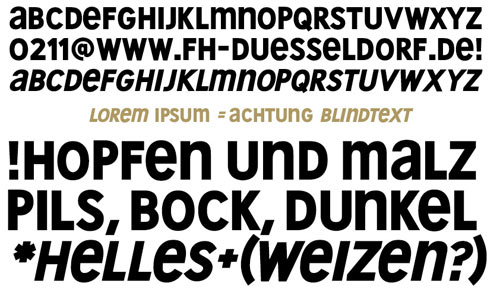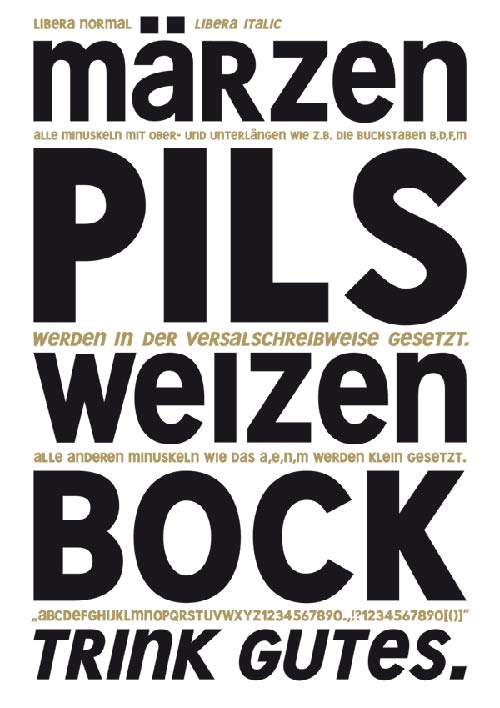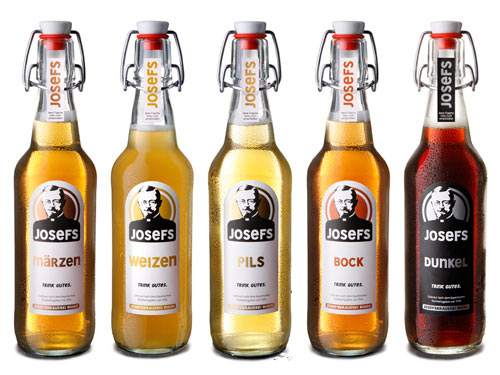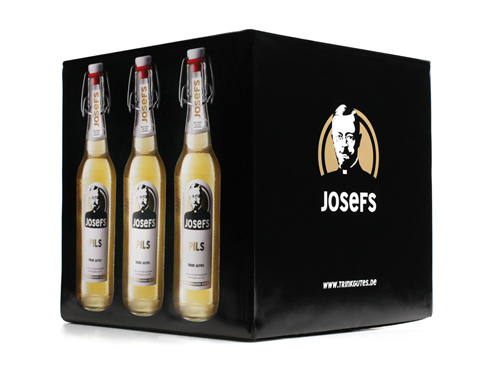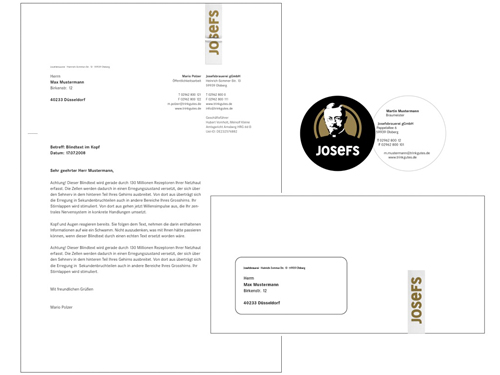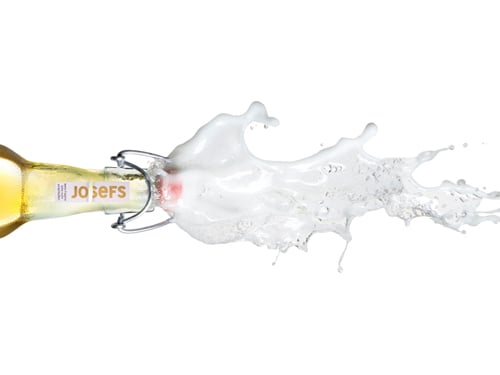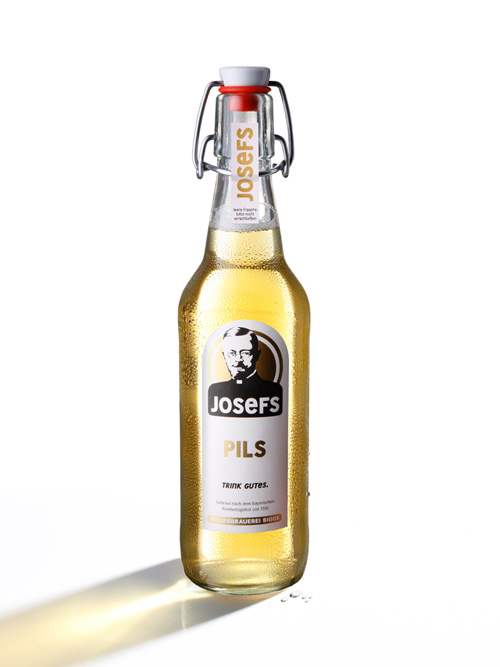
"Zum Wohl" Humberto Gregorio hat es geschafft, ihm Rahmen seiner Diplomarbeit, an der FH Düsseldorf, für die Josefsbrauerei in Bigge (Sauerland) nicht nur ein neues Corporate Design zu entwickeln, sondern auch eine neue Schrift "Libera". Die Josefsbrauerei in Bigge ist die erste Behindertengerechte Brauerei in Europa und wurde 2002 als Integrationsfirma gegründet. In Ihr arbeiten überwiegend Körperbehinderte Menschen.
Um dem Thema der Gleichstellung von Menschen mit Behinderung gerecht zu werden, entwickelte Humberto Gregorio seine Schrift "Libera" als reine Headline-Unicasefont (Mischung von Versalien und Minuskeln, welche keine unterschiedlichen Höhen aufweisen).
Die Auswahl der Buchstaben ob Versalie oder Minuskel folgt folgender Regel: Alle Buchstaben mit Ober- und Unterlängen wie z.B. b, d, oder f werden in der Versalschreibweise, alle anderen werden als Minuskel gesetzt.
Die Schrift wurde als Corporate Font für Headlines und Etiketten konzipiert. Da Humberto Gregorio während seiner Diplomarbeit keine passende Unicase fand, wagte er sich neben der Markenentwicklung für die Josefsbrauerei auch noch an den Schriftentwurf.
Momentan bekommt "Libera" noch den letzten Feinschliff und wird daher erst im Frühjahr 2009 fertig sein. Geplant sind neben den bereits existierenden Schnitten heavy und heavy italic noch ein „normal“ und condensed-Schnitt.
Die Biermarke wird aller Voraussicht im Spätsommer gelaunched.
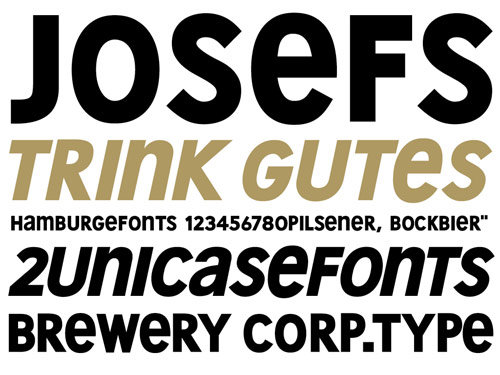
Da war schon viel Schönes bei ...
Die Gemeinen sind zu groß, ansonsten ziemlich 90er Jahre ...
90er? Finde den font ziemlich modern.
Um dem Thema der Gleichstellung von Menschen mit Behinderung gerecht zu werden, entwickelte Humberto Gregorio seine Schrift "Libera" als reine Headline-Unicasefont
aha?! ob allerdings diese (und ja, generell) unicase-schriften legastenikern behilflich sind, wage ich mal sehr zu bezweifeln - oder hab ich die ironie darin nicht verstanden?
und das corporate design an sich, ja, das geht in ordnung - auch wenn ich es eher in die »bionade«-ecke gestellt hätte, nicht zuletzt wegen dem che-guevara-portrait. aber die schrift finde ich jetzt nicht besonders gelungen. in diesem fall macht die unicase innerhalb von wörtern teilweise eine ziemlich ungünstige figur (s. »malz«, »märzen«, der kopf des »p«)
ja die gemeinen springen einen förmlich an. der rest meiner meinung nach eher durchwachsen und langweilig, bzw. gesehen. und damit ein diplom zu füllen. an anderen hochschulen wäre das zu wenig.
Bionade wäre wohl die erste Idee, die einem dazu einfallen würde. Bisschen flach oder?
Die Unicase als headlinefont zu nutzen ist ne gute Idee und müsste selbst Legastenikern nicht zu schwer fallen. Man denke mal an die gebrochenen, altdeutschen Schriften der anderen Biermarken.
Kann mir nicht vorstellen, dass du aus deinem Sessel beurteilen kannst, ob dies ein Diplom füllen kann. Das sind ja bloß paar Screenshots. Ball flach halten und zurück in die Provinz.
ich lese Jose FS. Das liegt daran das o, s und e ebenso Minuskelcharakter haben. Das Versal-S bricht die Serie dann auf und irritiert. Den gesamten Zeichensatz empfinde ich als zu unruhig und unausgeglichen, was sich dann in der Schriftanwendung z.B. in der URL beim .de zeigt. Ist der Herr auf dem Logo verwandt mit Lenin und Tschichold? =)
v.
Gast
...ganz ehrlich: die Schrift hat für mich eher Skizzen-Stadium. Die is einfach noch zu unsauber (Strichstärken, Neigungswinkel, Proportionen, besonders die Kursive rockt noch nicht). Den Bierspritzer find ich affig. Trotzdem für ne Studi-Arbeit feine Sache!
Gast
grandios dein werk!
finde ich manchmal schon recht amüsant wir bei slanted
kommentiert wird. ich nenne es "erudierte impertinenz".
man kennt das phänomen aus dem baumarkt. der kunde
fragt nach einem produkt und erklärt dann dem personal
rechthaberische, fachkundige begrifflichkeiten. zu schulzeiten
hat man dazu gesagt: "ey du klugscheisser/ besserwisser...".
naja dar man einfach nicht ernst nehmen diese kommentare!
in diesem sinne alles gute!
daniel perraudin
Und wegen dem "Übersehen": die jeweiligen Inhalte sind ja sehr deutlich ausgezeichnet. Auch das Ganze drumherum ist ja sehr deutlich und macht klar: es gibt verschiedene Biere, was ja durch das Klarglas auch nochmals sichtbar wird.
Das Wichtigste ist, dass das Bier ein feines ist, wenns scheisse schmeckt, würd ich mich auch nicht so weit rauslehnen. Aber als Diplomarbeit ist das doch wunderbar. Und wer schonmal Bier fotografieren musste weiss: Good Job! Nur den Ferkelpastor Onkel Josef, finde ich ein Wenig arg, aber vielleicht ist es ja genau das.